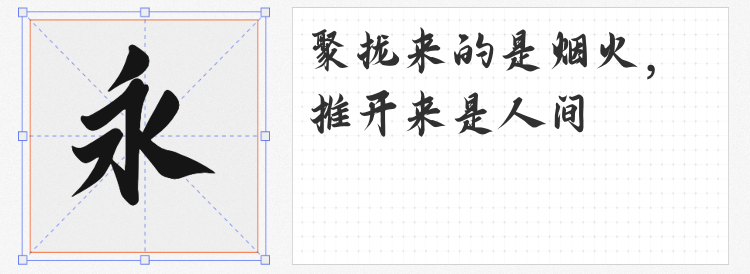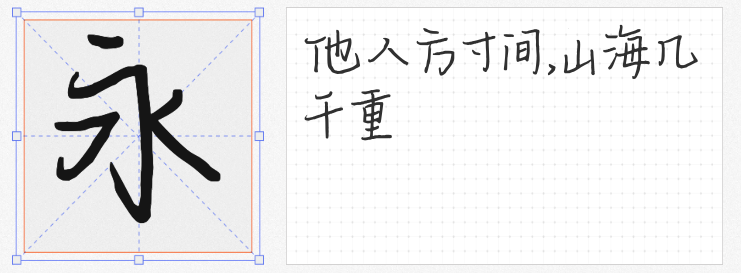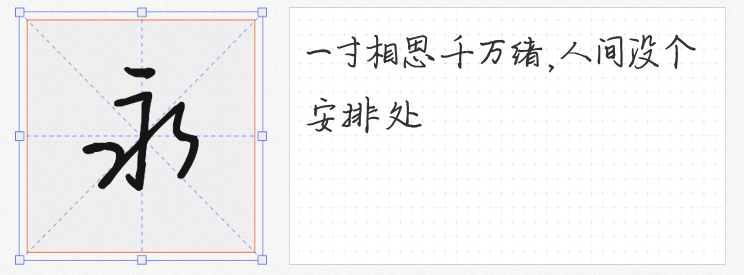
在数字化设计盛行的今天,手写字体的独特质感能为作品注入鲜活的生命力。无论是传递品牌温度的包装设计,还是彰显个性的海报标题,一款合适的手写字体都能成为点睛之笔。以下四款免费商用字体,以不同的书写风格与情感表达,为设计师提供多元化的创意选择。
这款字体以重庆“山城棒棒军”这一即将消失的职业为灵感,笔画粗犷有力,结构错落有致,仿佛挑夫肩头的扁担与绳索,带着山城的烟火气与劳动者的坚韧。由于未包含英文、数字及符号,它更适合作为中文标题或短文案的视觉焦点,例如在纪录片海报中书写“最后的棒棒”,搭配老照片背景,瞬间唤醒观众对城市变迁的共鸣。其不规整的笔画边缘,也为复古风设计增添了手工制作的质朴感。
以硬笔书法为基底,平方上上谦体的线条纤细却富有张力,连笔处自然流畅,兼具行书的洒脱与楷书的工整。这款字体适合需要平衡“正式感”与“个性表达”的场景,如品牌slogan、社交媒体文案或手账素材设计。例如,在咖啡包装上用上上谦体书写“慢煮时光”,搭配简约线条插画,既能传递产品调性,又避免过于甜腻的手写风格。
平方三生体的笔触更显轻盈,如同用细毛笔勾勒的现代书法,字形结构疏密有致,适合需要突出“精致感”的设计场景。其应用范围广泛,从文艺类海报标题到品牌字帖设计均能驾驭。例如,在女性护肤品广告中,用平方三生体书写“柔光如初”,搭配水彩渐变背景,可强化产品“温和天然”的视觉联想。
平方韶华体的笔画粗细介于平方上上谦体与平方三生体之间,既保留了手写的灵动,又兼顾了远距离阅读的清晰度。其均衡的视觉重心,使它成为长文案排版的理想选择,如活动邀请函、书籍封面副标题等。例如,在毕业季海报中,用平方韶华体书写“青春不散场”,搭配校园风景摄影,能精准传递温暖而不煽情的情感氛围。